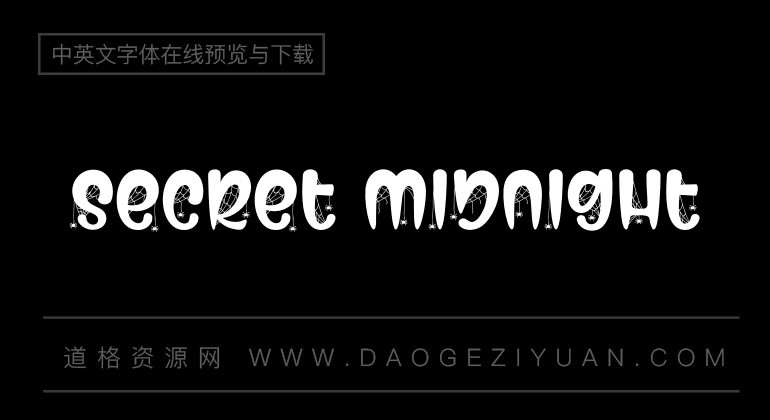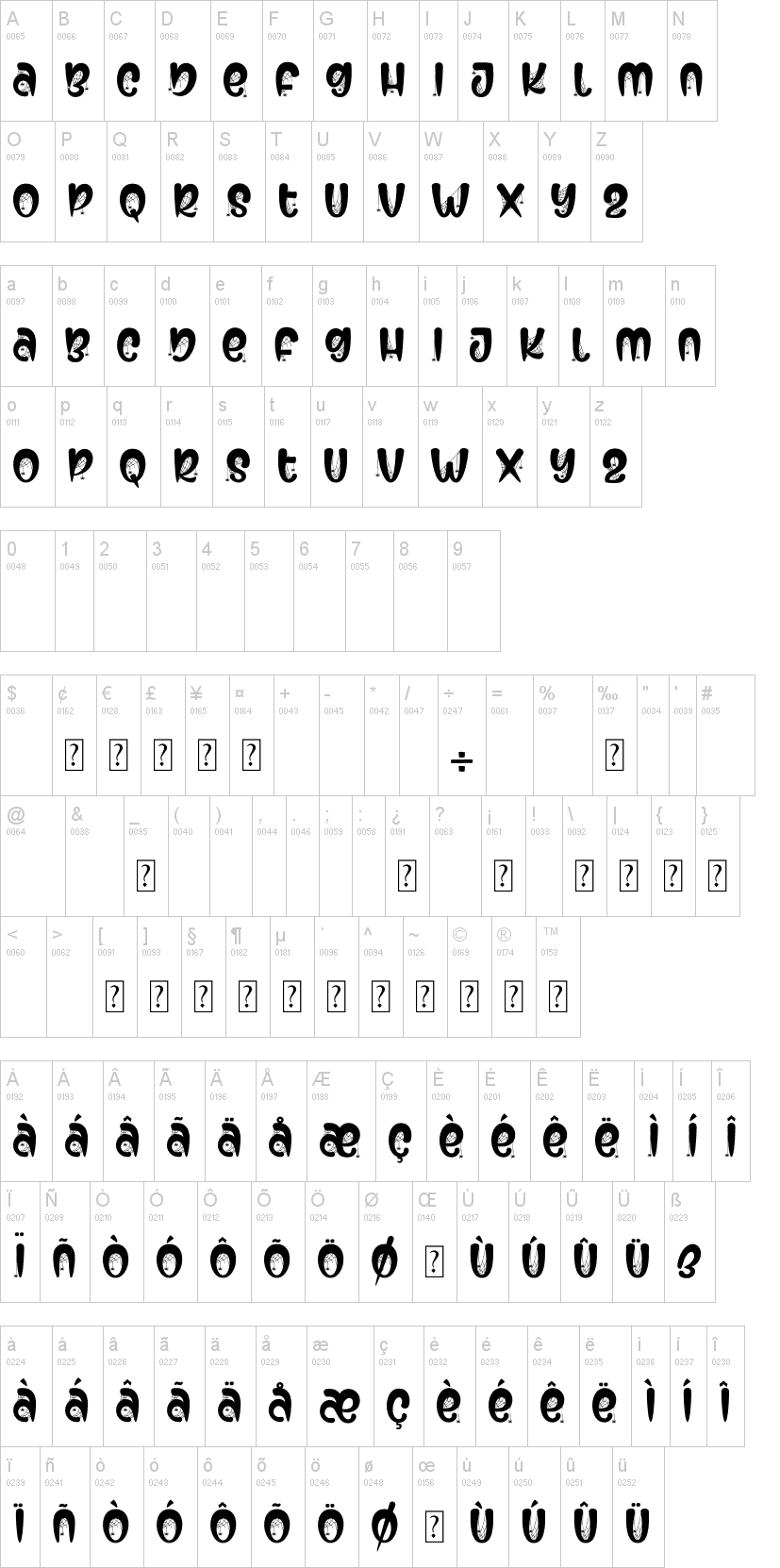
Secret Midnight
Secret Midnight 是一款新潮的手写体字体,它具有粗犷的笔画和大胆的设计,给人一种活泼而温暖的感觉。它的特点是笔画粗细不一,每个字母都有自己独特的形状,使得它充满了活力。它可以用于各种印刷品,如书籍、海报、海报、杂志等,也可以用于网页设计中,特别适合用于活动宣传等。
Secret Midnight是一款非常不错的手写艺术字体,具有很好的视觉感,适合于文化类的宣传设计、商业类品牌的广告和产品包装设计以及个性化文字排版等较多场景。
Secret Midnight字符映射图